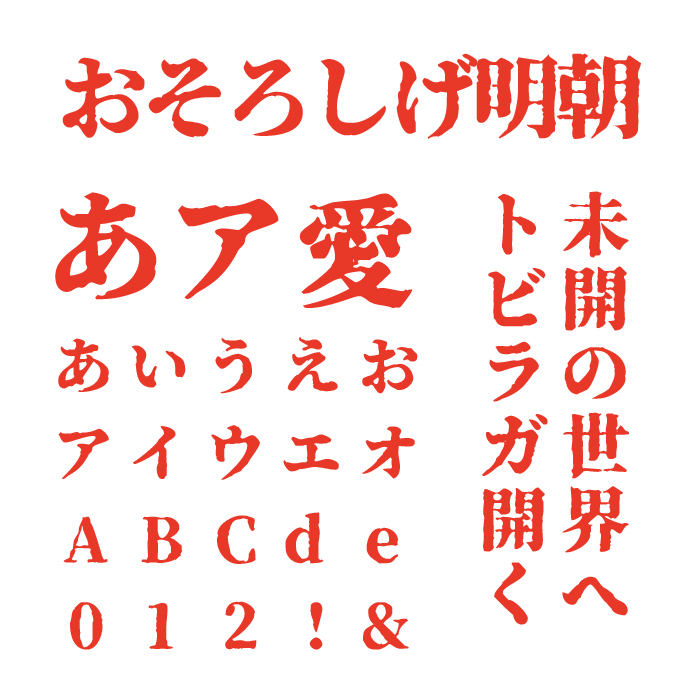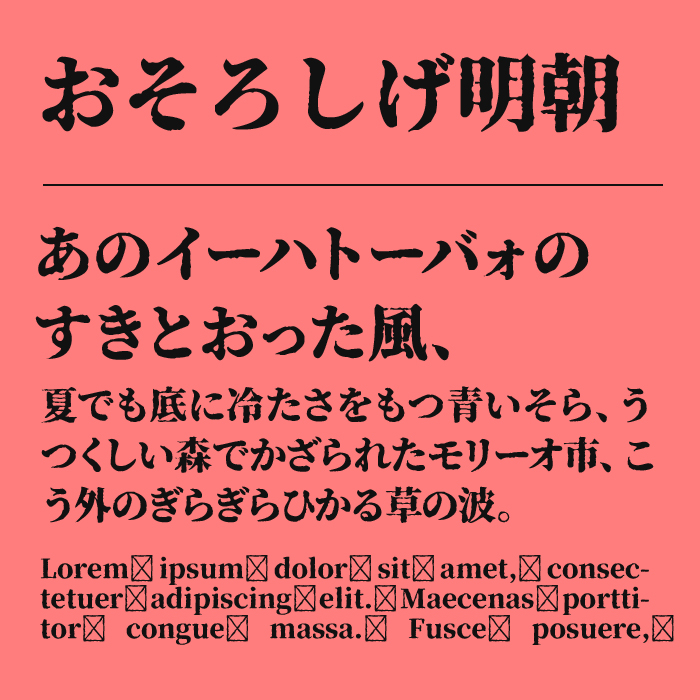
おそろしげ明朝フォントは、Noto Serifフォントをベースにインクの擦れや欠けを加えた、不気味さと味わいのある明朝体フォントです。
縦線の力強さと横線の細さがはっきりしていて、文字の端が少し崩れているので、古びた紙に書かれたような雰囲気が出ます。見出しに使うと一文字一文字が強く印象に残ります。
ホラーや怪談、民俗学などのテーマに特によく合います。イベントのポスターや怪談朗読の告知に使えば、見た瞬間に「怖そう」という気分を盛り上げてくれる雰囲気をもつフォントです。ほかには歴史や伝承を扱うコンテンツにもぴったりです。
収録文字は、漢字・ひらがな・カタカナ・アルファベット・数字・記号が収録。
| 収録文字 | ひらがな/カタカナ / 漢字 / 英字 / 数字 / 記号 |